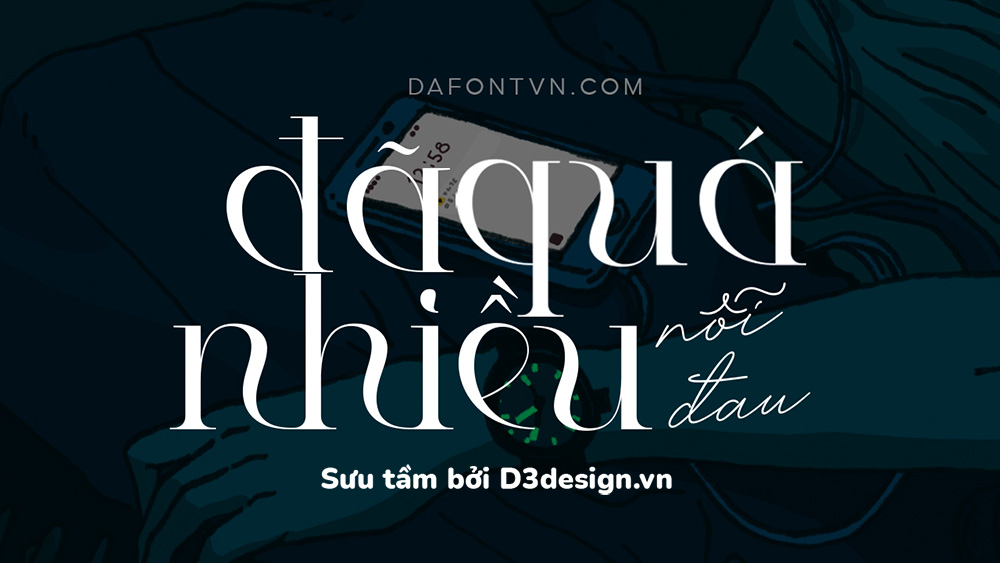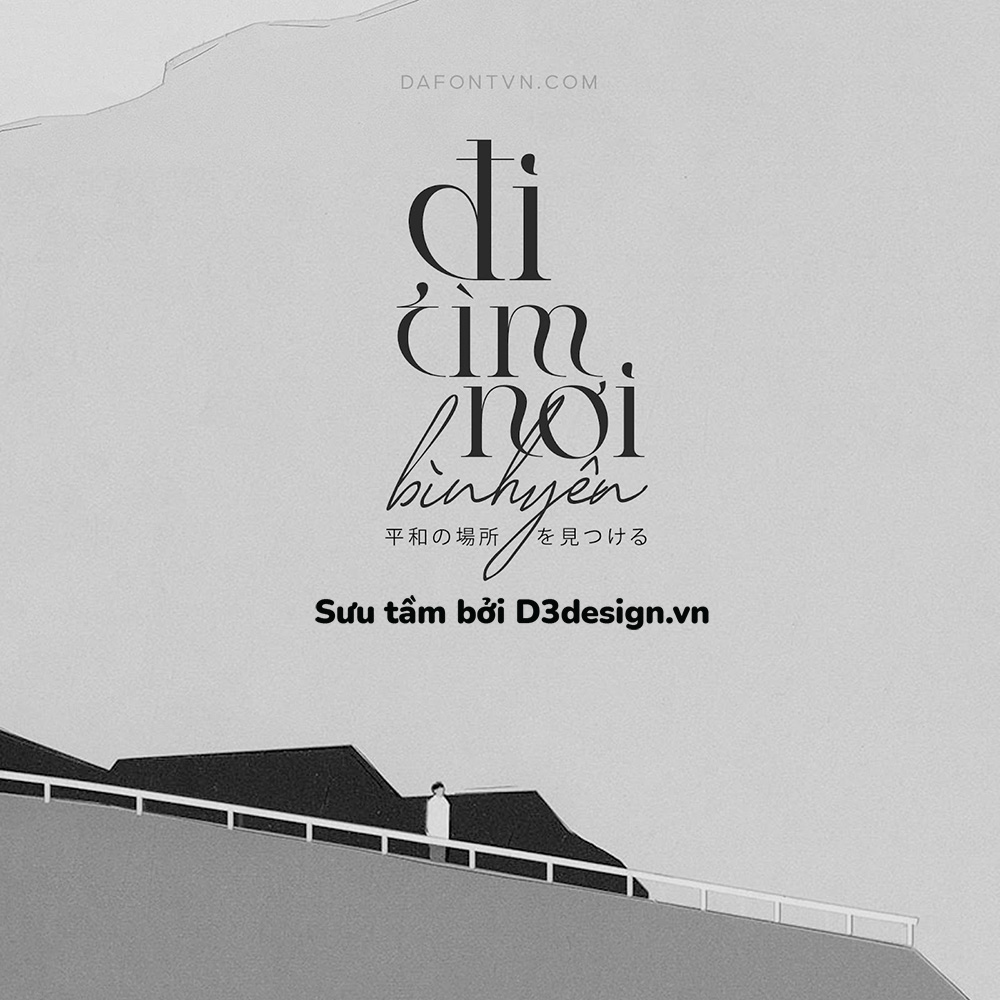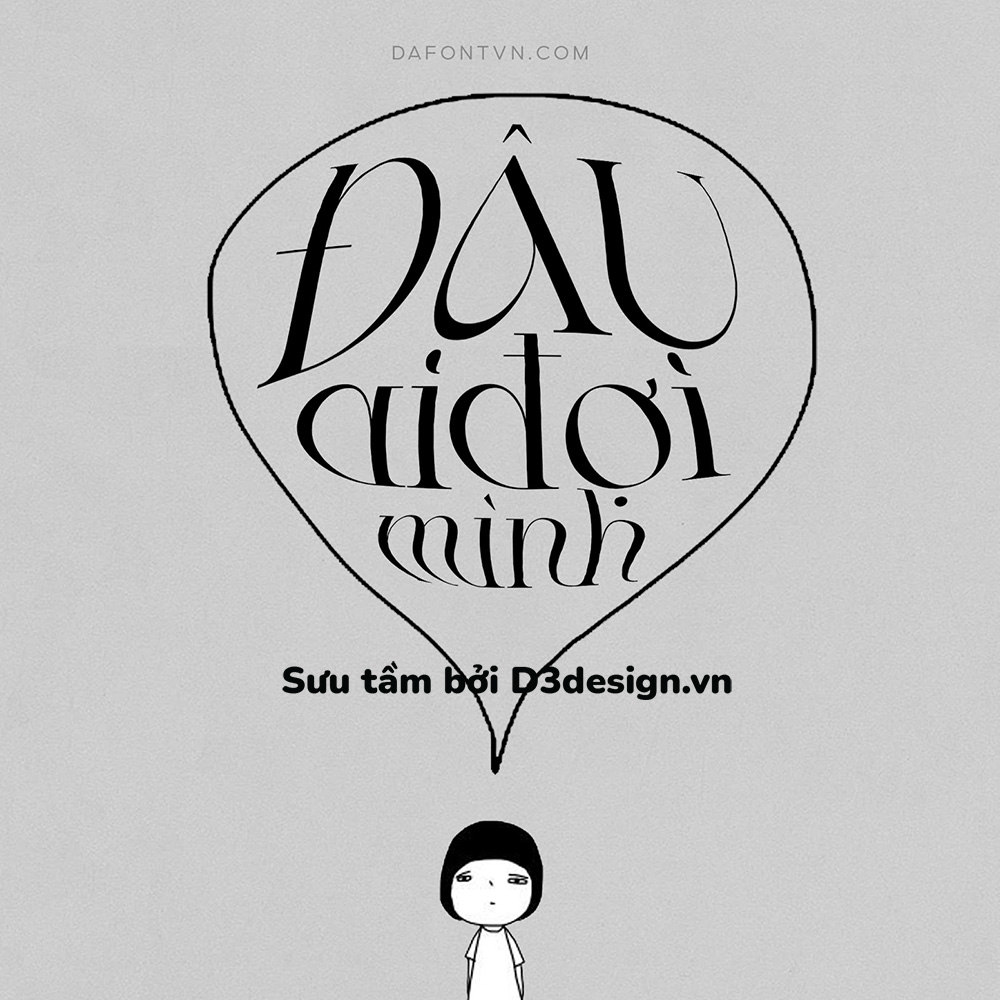
Font Việt Hóa - Philosophy Mang Phong Cách Hiện Đại Và Tinh Tế
Philosophy 1 kiểu serif độc đáo với các đường nét cực kỳ ấn tượng, các chữ cái được thiết kế mới lạ và đẹp mắt vì vậy bạn có thể sử dụng nó cho rất nhiều các thiết kế khác nhau. Bạn có thể sử dụng font này cho các thiết kế như thiệp mời, logo, quảng cáo, typography, trích dẫn...
Font Philosophy việt hóa và kerning đầy đủ, ngoài ra 1 số dấu và các khoảng cách được chỉnh sửa lại để hoàn hảo hơn.